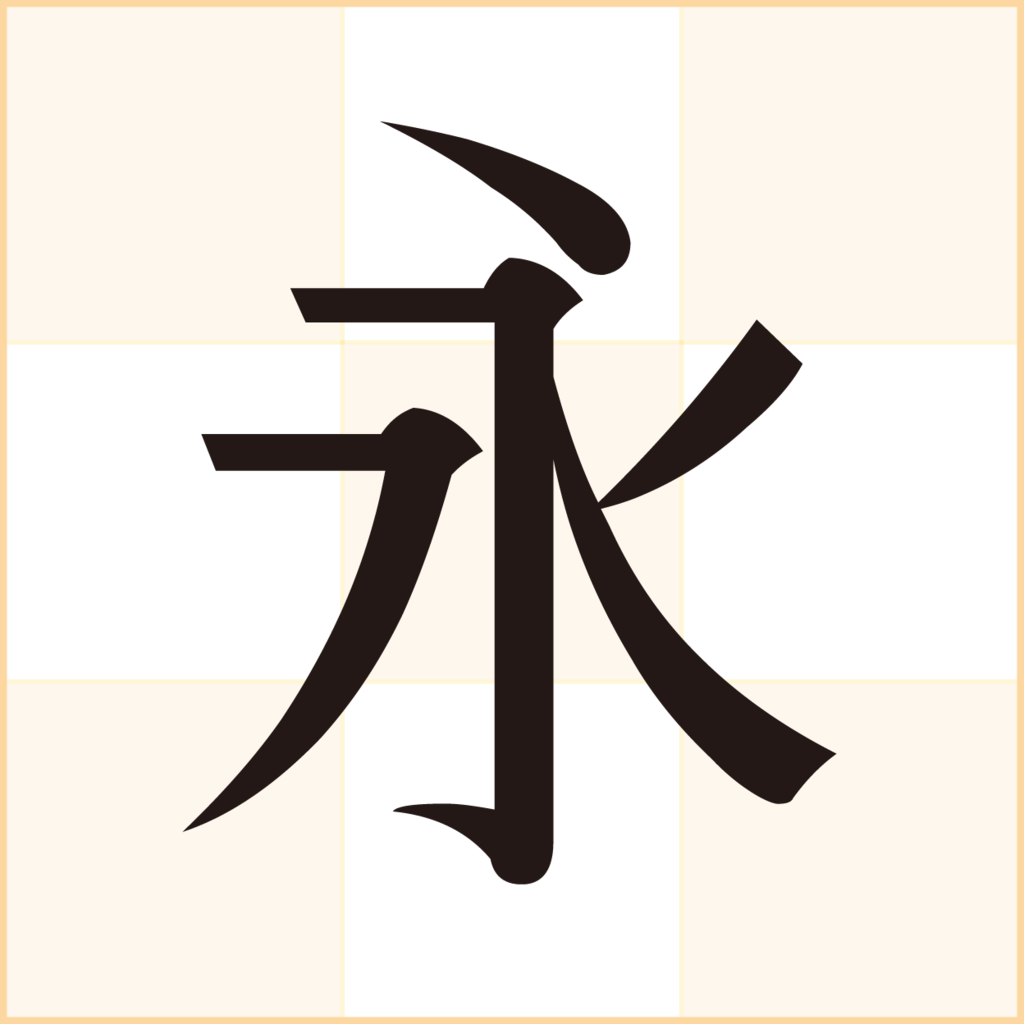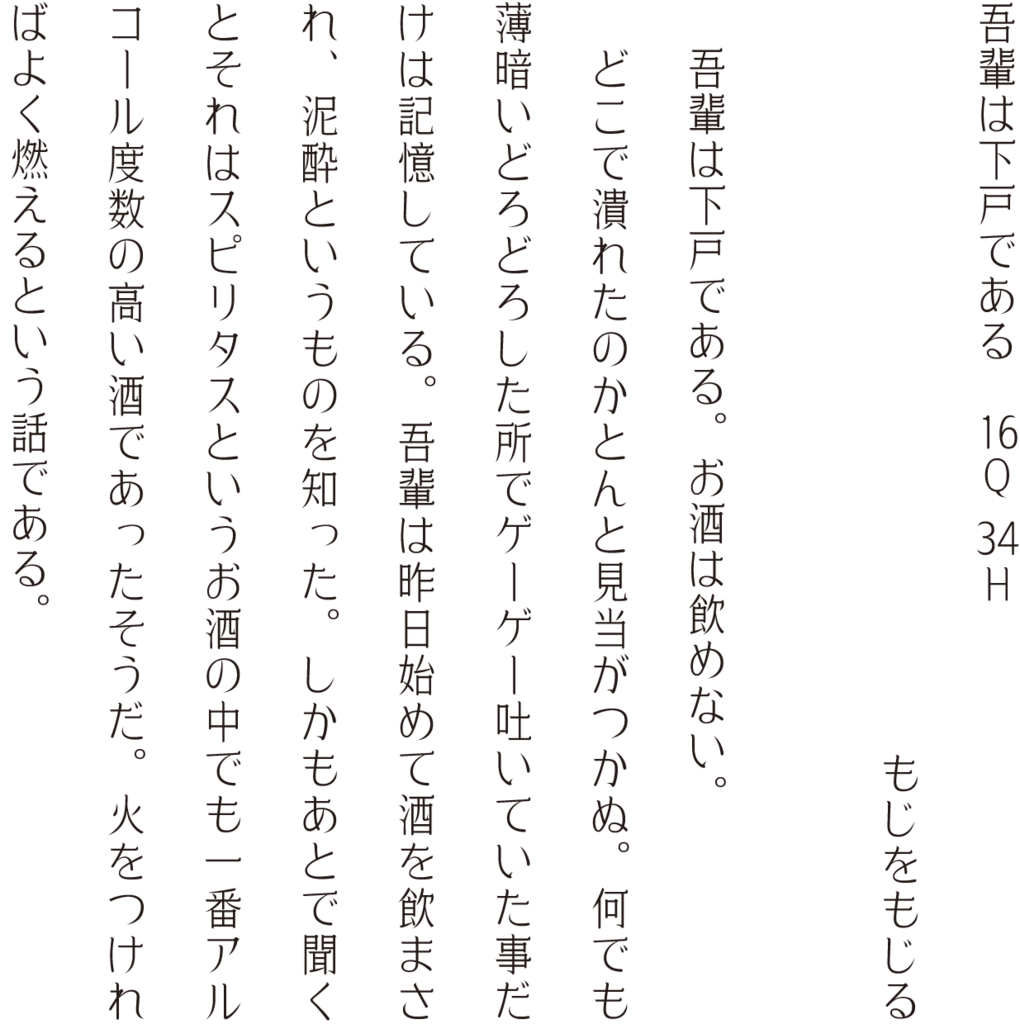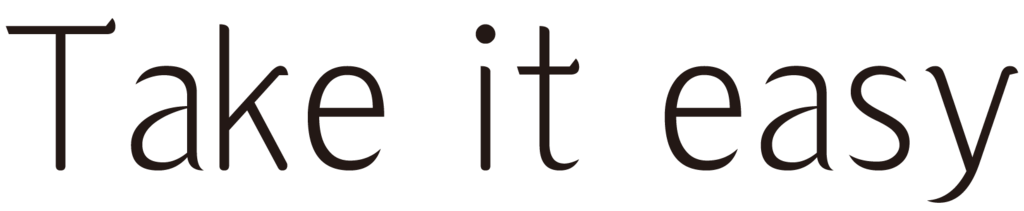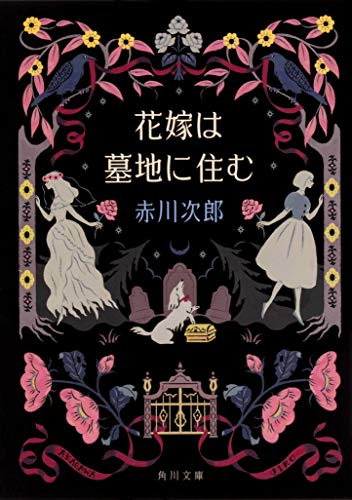
娥眉明朝体
資生堂書体とも似ている、どことなく女性的なイメージの明朝体。
娥眉明朝体の組見本(W3)
新元号「令和」の娥眉明朝体書体見本
新元号「令和」の娥眉明朝体の書体見本。
娥眉明朝体使用事例「魔女の泉3 Re:Fine ―人形魔女、『アイールディ』の物語―」
株式会社スタジオアートディンクが2020年12月17日にリリースしたNintendo Switch用ゲーム「魔女の泉3 Re:Fine ―人形魔女、『アイールディ』の物語―」に、ダイナフォント「娥眉明朝体」が採用されている。
採用理由はシナリオの深みを表現でき、ゲームの雰囲気を強調しつつも優雅さを感じられるため。また、ゲームの穏やかで暖かい雰囲気に似合うのはもちろん、可読性も良いこと。
娥眉明朝体使用事例「花嫁は墓地に住む 花嫁シリーズ」
「花嫁は墓地に住む 花嫁シリーズ」の表紙タイトルの文字に娥眉明朝体が使用されている。